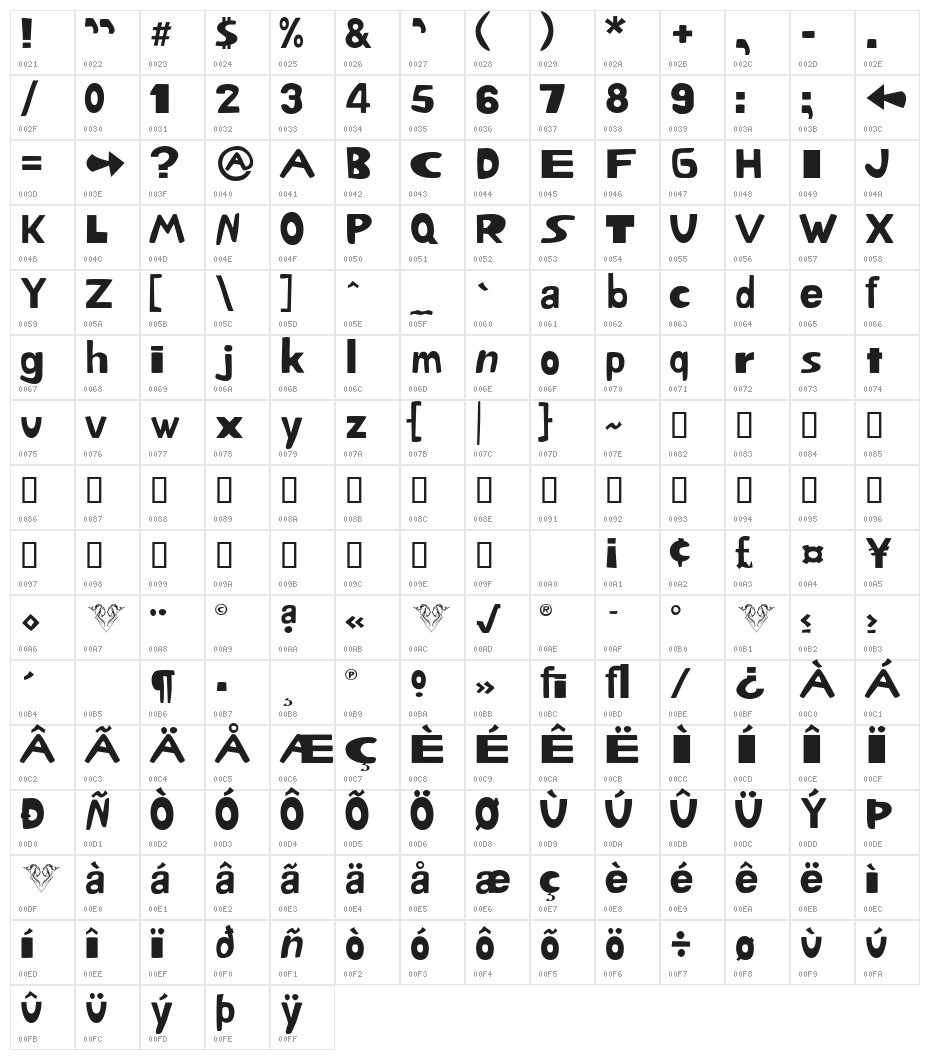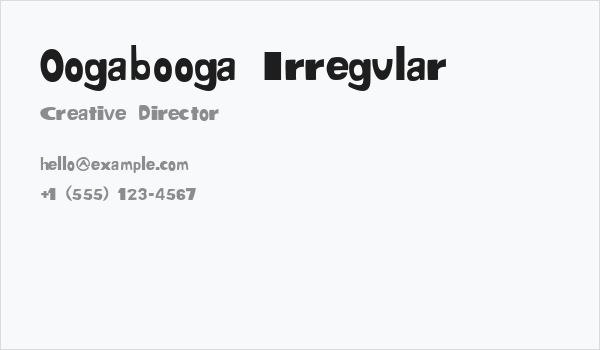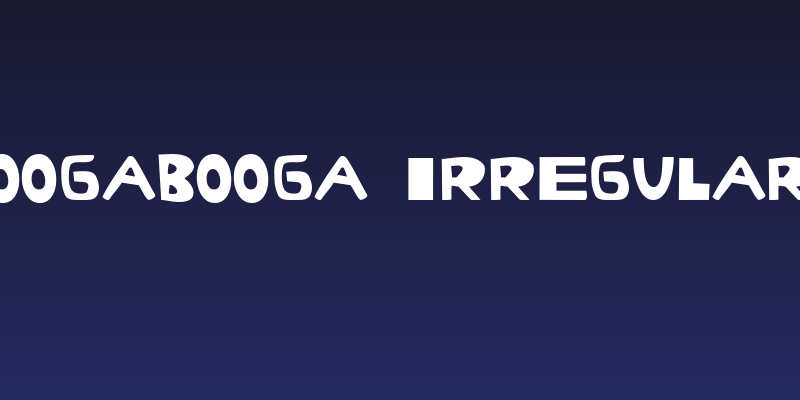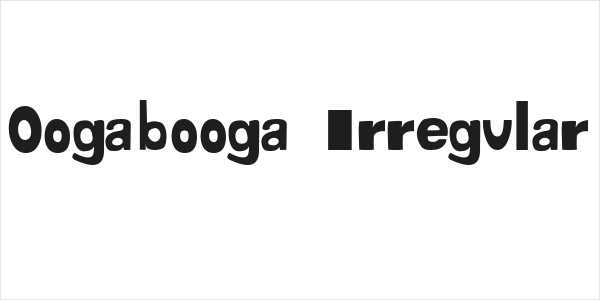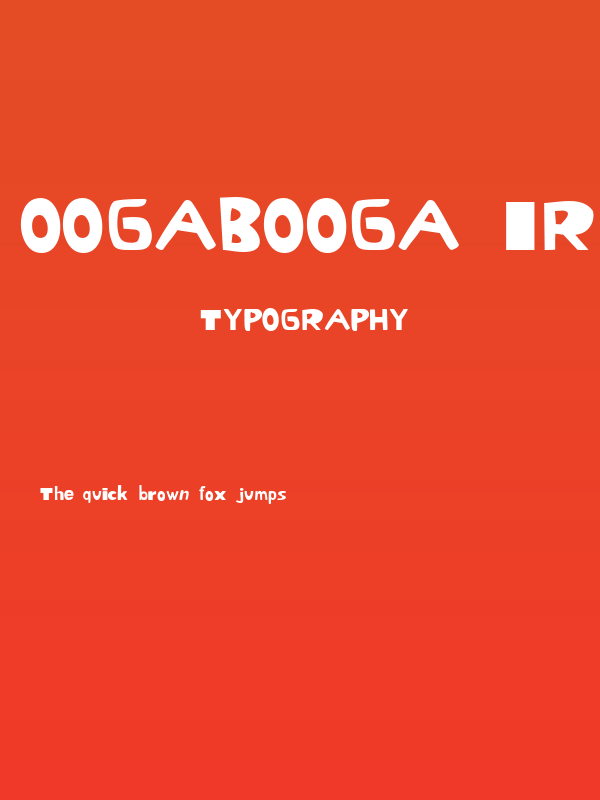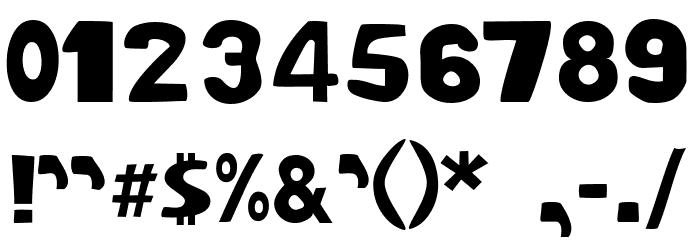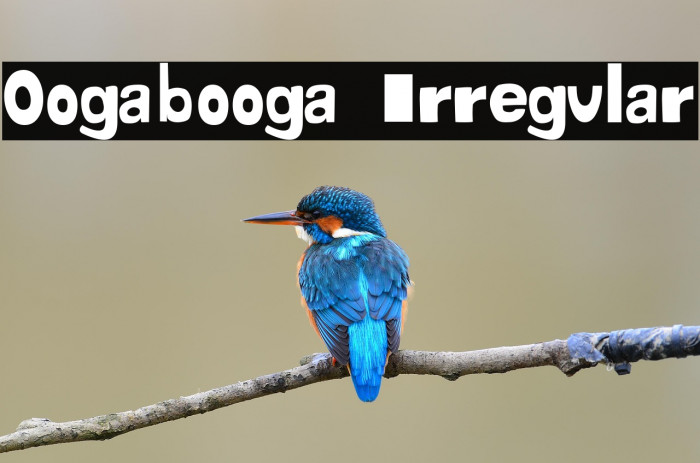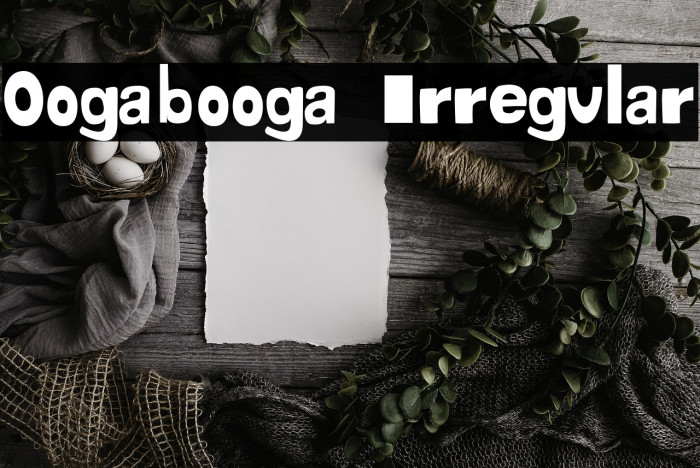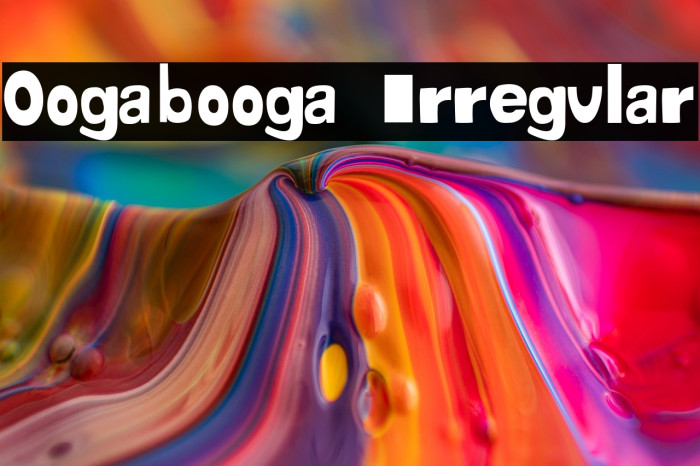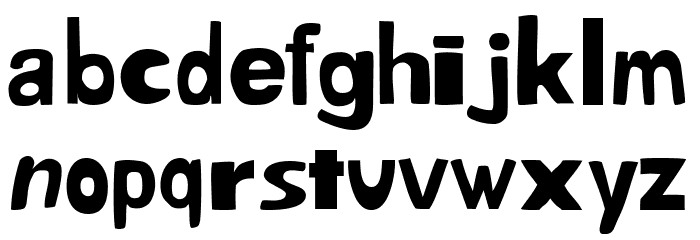
Oogabooga Irregular Font
| Style général | Playful |
| Cas d'utilisation | Logos, Posters, Creative projects |
| Projets proposés | Ideal for children's books, playful branding, creative posters, and informal invitations. |